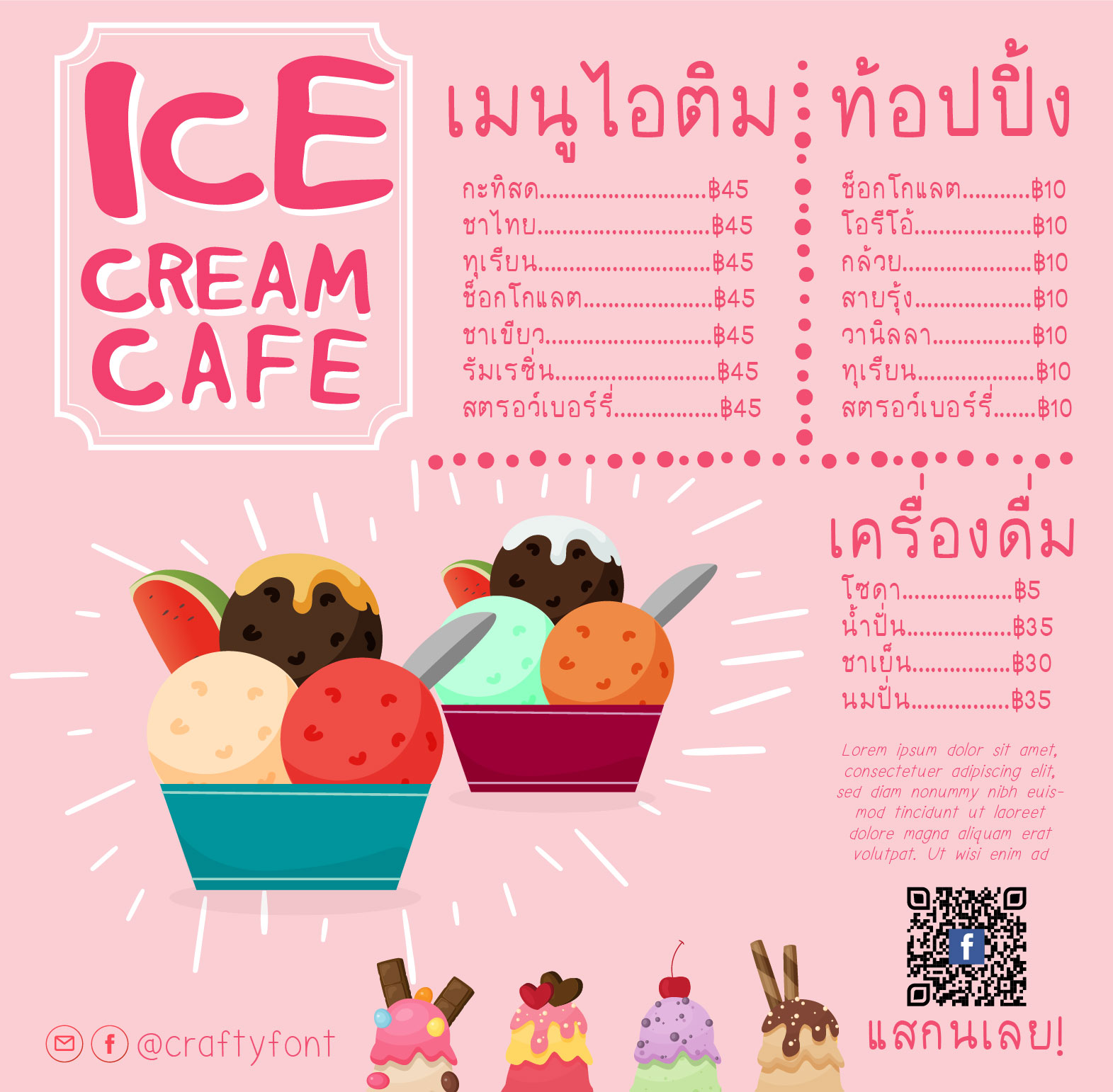
ไอติม (ice cream)
ภาพแรก ฟอนต์ไอติม:
ฟอนต์ไอติมออกแบบมาให้เป็นฟอนต์มีหัว แต่ทำให้หัวเล็ก บีบตัวอักษรให้แขบลง (กว่าที่ Crafty font เคยทำ) ให้ความรู้สึกเป็นมิตรมากขึ้น!
ฟอนต์น้องไอติมมีทั้งภาษาไทยและภาษาอังกฤษเลยนะคะ แฟมิลี่เซ็ตนี้มี 4 ขนาดด้วยกัน ทั้งตัวหนา ตัวเอียง ตัวบาง และตัวปกติ สัญลักษณ์บวกลบคูณหารมีให้ใช้ครบ ฝากไว้ในอ้อมอกอ้อมใจพี่จ๋าด้วยนะจ๊ะ